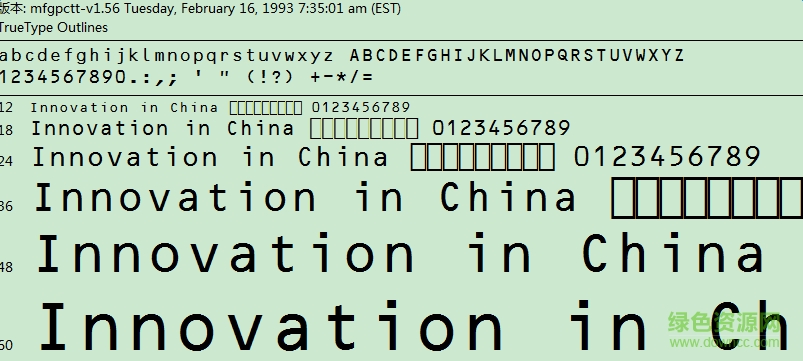
Hiddenhorzocr是一款Adobe Acrobat professional軟件中Touchup的默認字體,字體端正有型,符合多種漢字規(guī)范,喜歡的朋友來綠色資源網(wǎng)即可下載哦!
Hiddenhorzocr是adobe acrobat中的嵌入型字體,屬于系統(tǒng)默認字體,給你比較舒適的視覺呈現(xiàn),很多朋友在獲取改字體時都出現(xiàn)錯誤或亂碼情況,今天在綠色資源網(wǎng)大家便可獲取完整版!